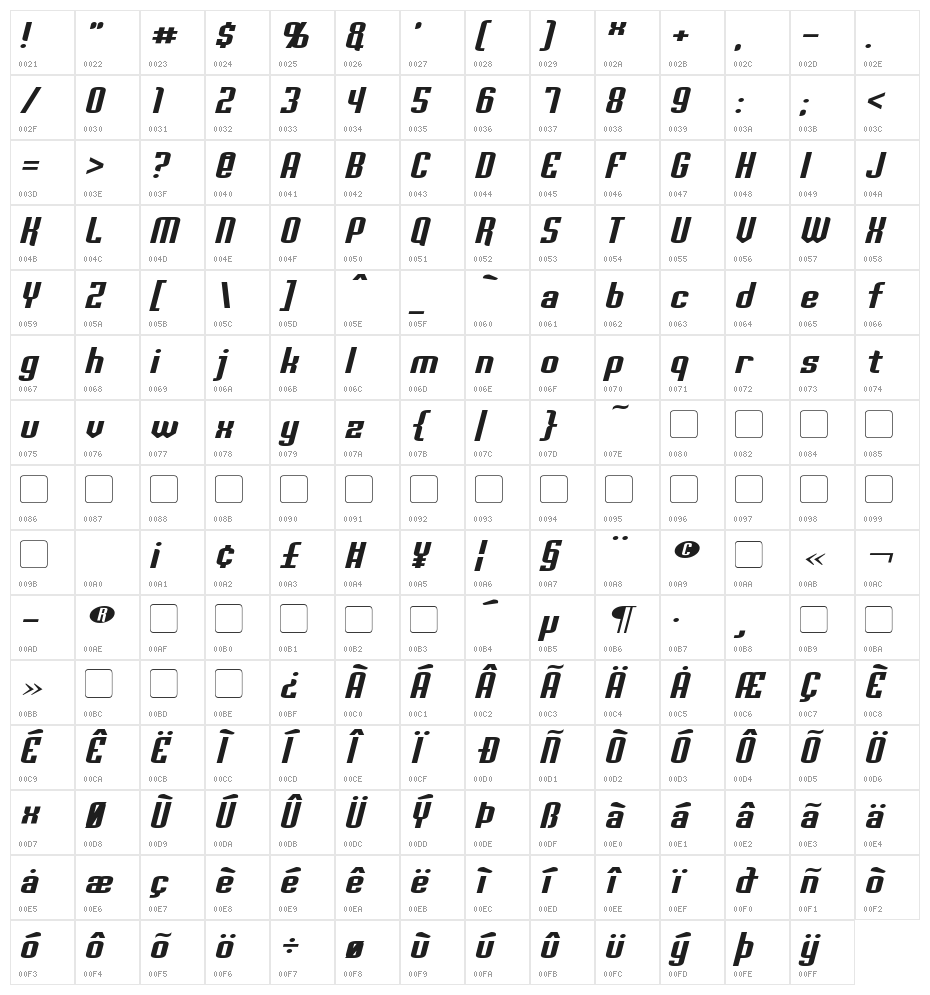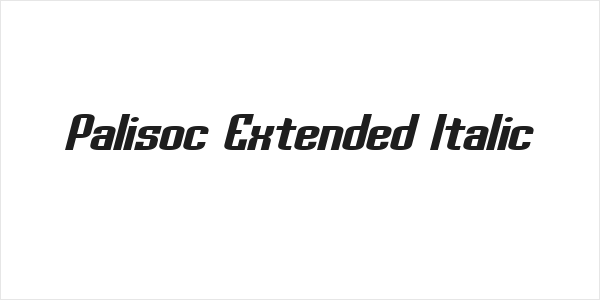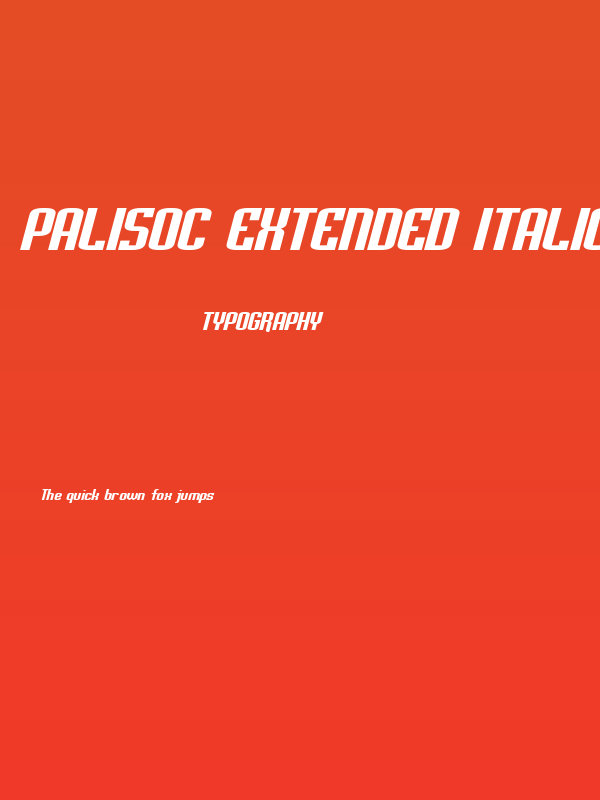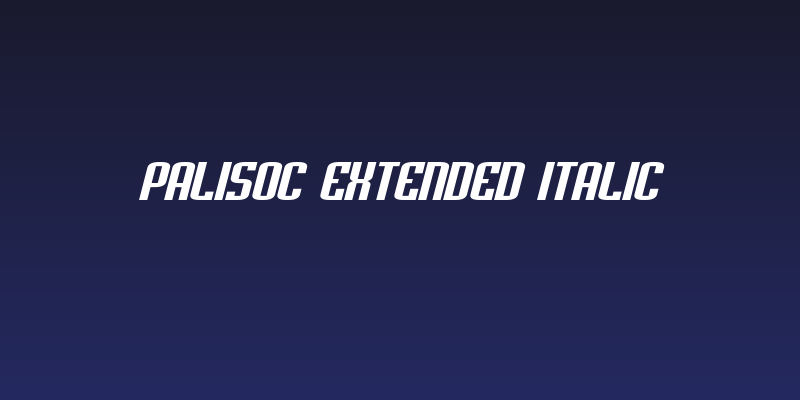
Palisoc Extended Italic Font
| Nome | Palisoc Extended Italic |
| Peso | Italic |
| Larghezza | Expanded |
| Progetti proposti | Ideal for branding, advertising, posters, and headlines where a strong and contemporary look is desired. |